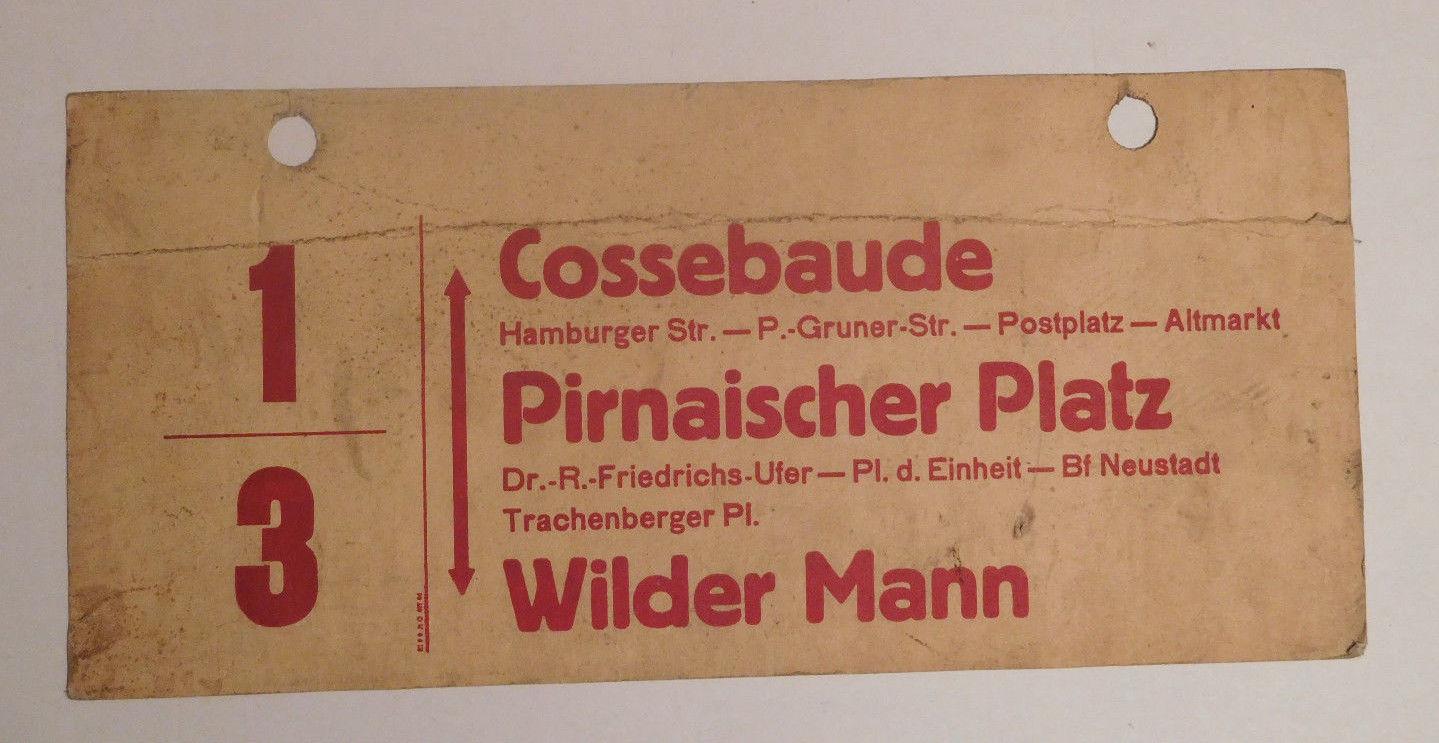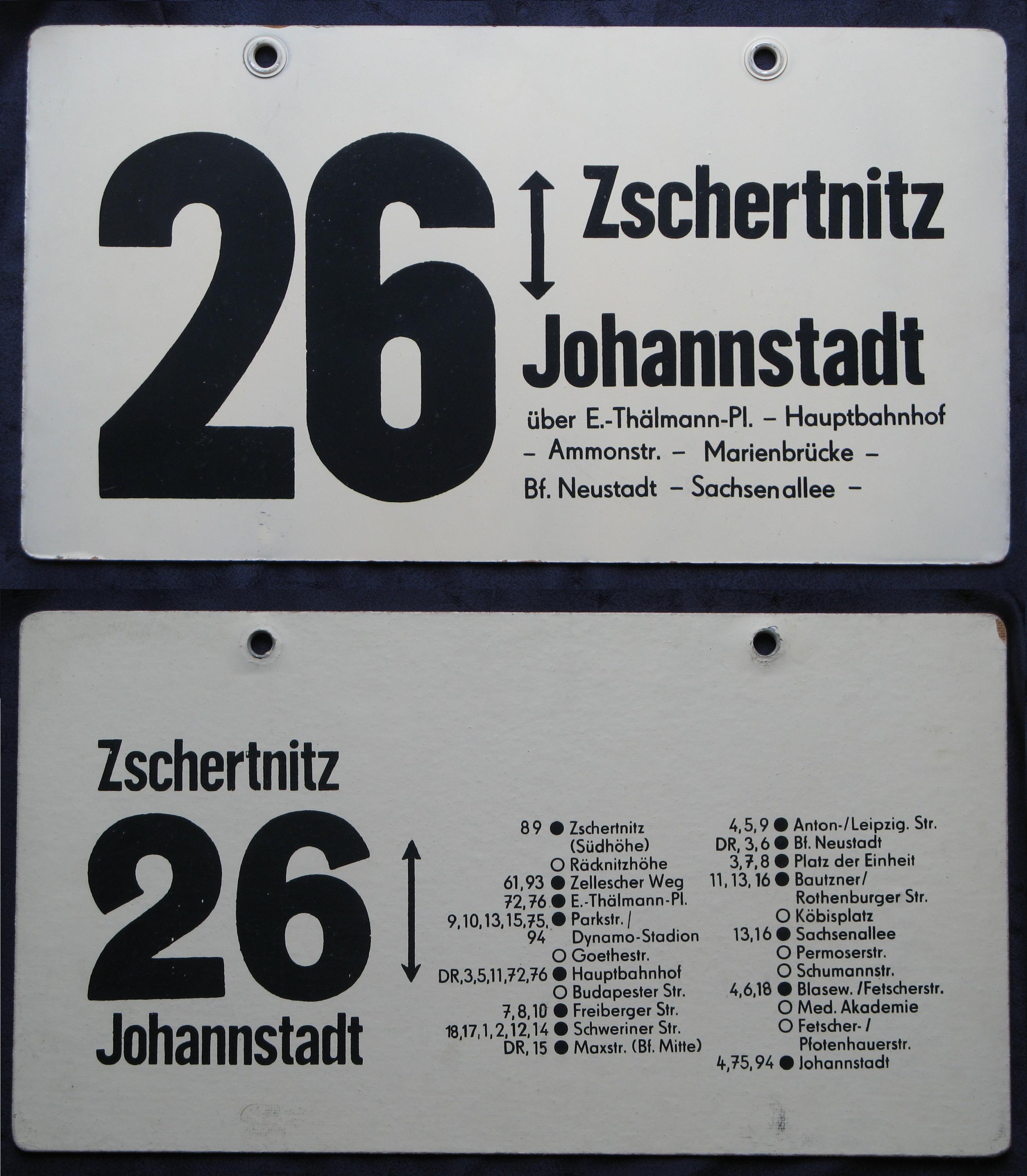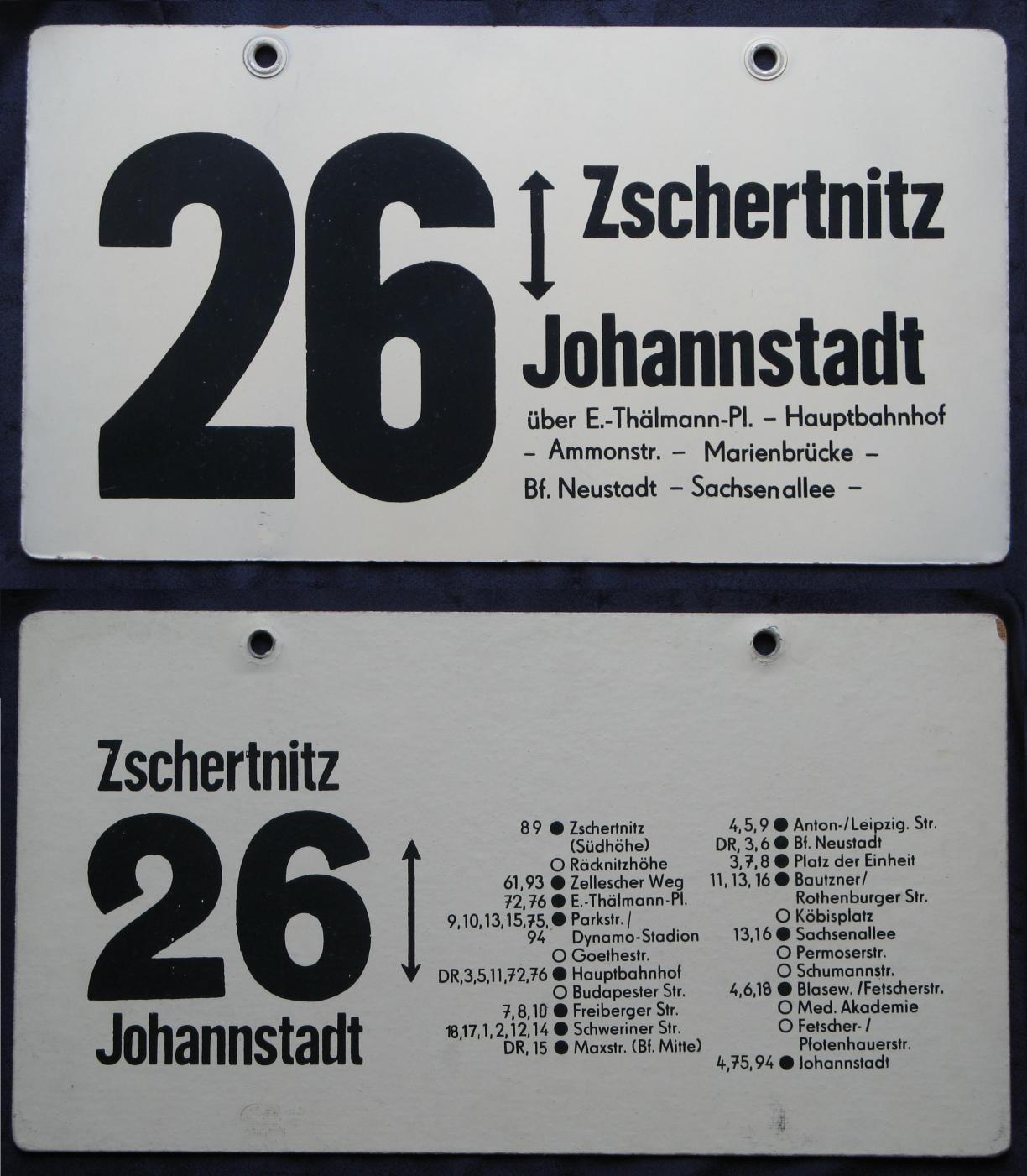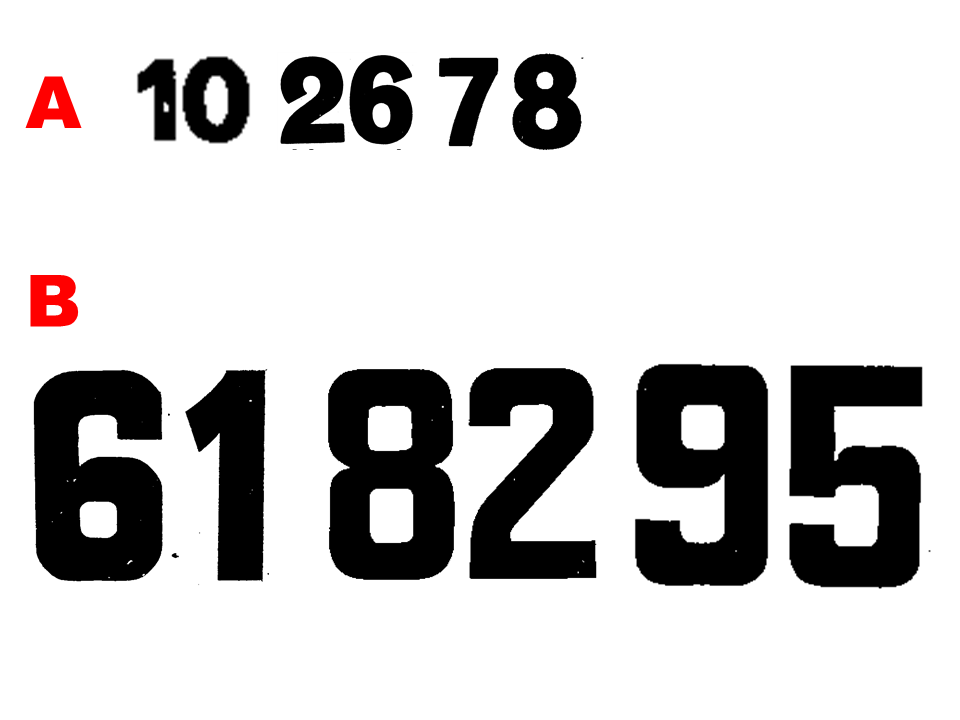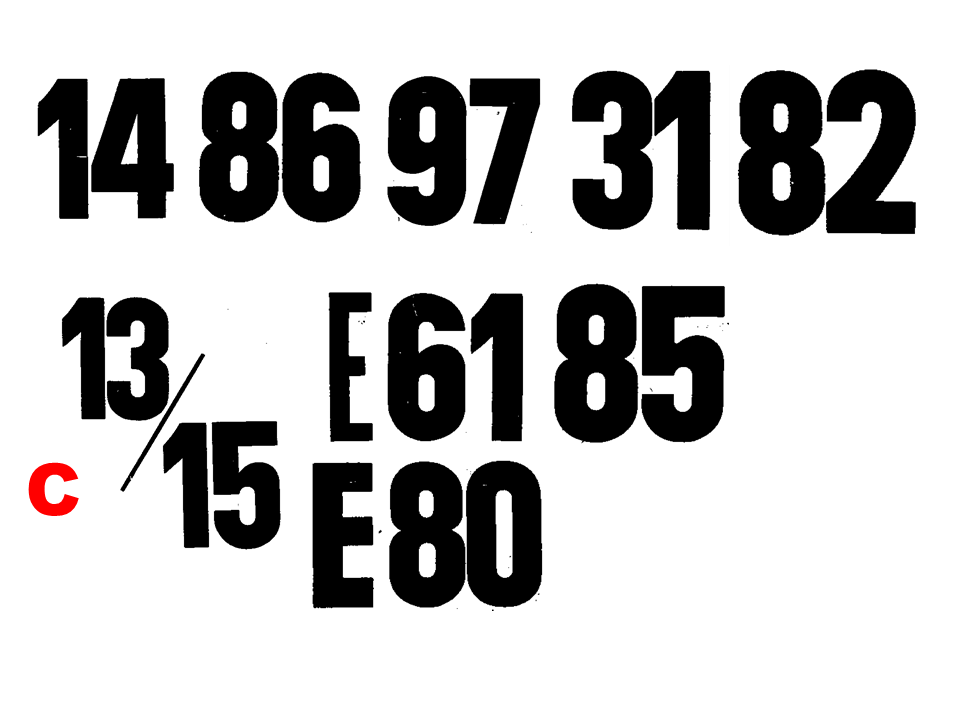
Linienschilder Dresden (80er Jahre)
ich bin auf einige Linienschilder aus Dresden gestossen. Ich selbst weiss, dass ich ein Linienschild zu Hause habe, welches mit Hilfe eines Siebes auf eine lackierte Hardfaserplatte »gespachtelt« wurde. Später gab es dann auch diese auf Plaste. Die normale Schrift wurde in der Plak gesetzt. Nun suche ich den Namen der Schrift, welche für die Zahlen als Pate stand. Es sind drei verschiedene Zahlenmuster verwendet worden.
Wie fast immer in solchen Fällen wurde da wohl keine Satzschrift direkt benutzt, sondern irgendjemand in der Schilderwerkstatt hat einfach Schablonen geschnippelt/geschnitzt/gemacht und sich dabei bestenfalls grob an existierenden Satzschriften orientiert. Man sieht ja wie ungelenk viele Ziffern, besonders in Mustern B und C, sind. Das war Handarbeit.
Die schwanenhälsige 2 aus Muster A ist allerdings allerliebst! Von der ausgehend darf gern einer unserer enthusiastischen Fontschmiede einen Ziffernfont, nun ja, schmieden. ;-)
genau den Gedanken hatte ich auch
Vielleicht klappt es ja. Habe leider nur die Ziffern unter A) - aber ich schaue mal nach, ob sich nochmehr ansammelt
Die 2 erinnert mich ein wenig an die KABEL
Macht Sinn, denn ohne Kabel fährt keine Straßenbahn und auch keine E-Lok ;-)
die erste 26  wirkt wie die hier
Zschertnitz im ersten Schild wirkt wie die hier, wenn man den I-Punkt runden würde
<OT>Die hat auch Ähnlichkeit mit der Schrift von den Abreißkalendern mit den Sprüchen auf der Rückseite.</OT>
Das Wort Neustadt und Hauptbahnhof wirkt wie diese hier
Die Drescher passt, die Plak auch. Ich tendiere auch in Richtung einer Grotesk Nr. 9 (in der Art) Schrift, da diese sehr oft verwendet wurde. Wobei »Cossebaude« keine Grotesk zu sein scheint
Cossebaude scheint die hier zu sein. sie wirkt so.
möglich dass es auch noch schärfere versionen gibt.  schau mal im bild oben rechts sind noch mehr fundstellen aufgeführt. wenn du öfter sowas hast dann lohnt sich wahrscheinlich die suche mit diversen  Schrift-Indentifizierern (Matchator z.B.
Da die Dresdner in der Stadt Typoart hatten, schau ich immer in diese Richtung. Es würde nahe liegen. Aber wie schon erwähnt, Schildermacher waren kreative Menschen im Zeitalter ohne Computer.
Das kleine »z« mit der Spitze ist sehr speziell.